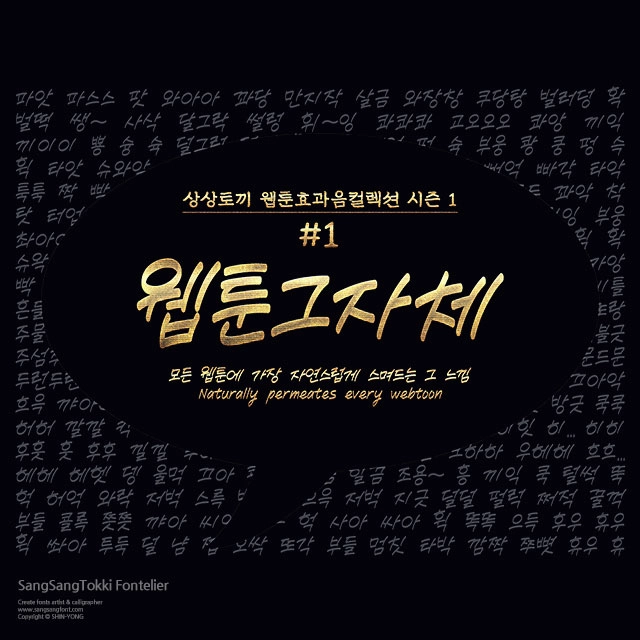
웹툰그자체
상상토끼의 웹툰효과음컬렉션 시즌1 첫번째, 웹툰그자체
#1 웹툰그자체 가장 일반적인 스타일로 일상물이나 스포츠물의 효과음등 대부분의 웹툰에 전반적으로 잘 어울리는 웹툰그자체입니다. 부드러운 외곽선을 사용했지만, 임팩트 있는 장면에도 위화감 없이 잘 어울리기 때문에 잔잔한 일상물에서부터 스피디한 액션물까지 무난하게 사용 가능합니다.